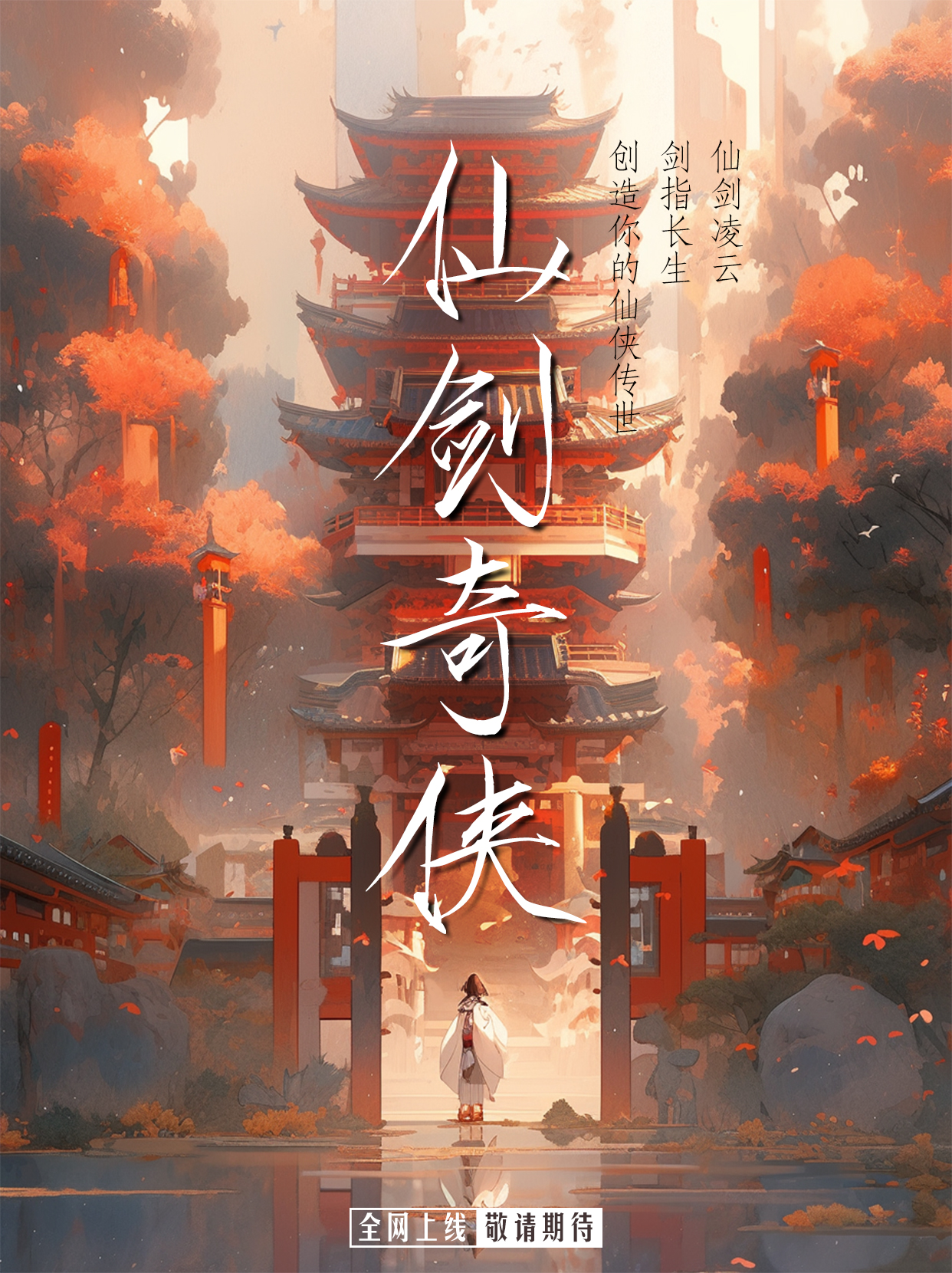
龙书法杨永志瘦金行楷体
Loong-ShoujinxingGBT
字体名称:
龙书法杨永志瘦金行楷体
字体语言:
简繁
书体类型:
楷体
字体类型:
普通字体
字体字重:
常规(Regular)
龙书法杨永志瘦金行楷体
字样介绍
瘦硬有神,用笔细劲,结体疏朗,横画收笔带钩,竖划收笔带点,撇如匕首,捺如切刀,竖钩细长。